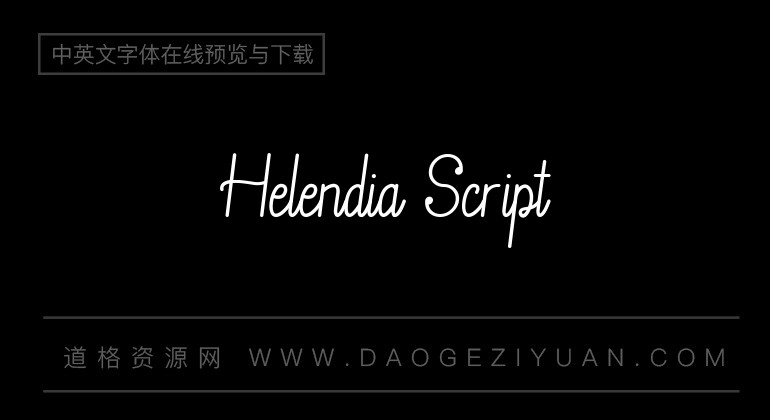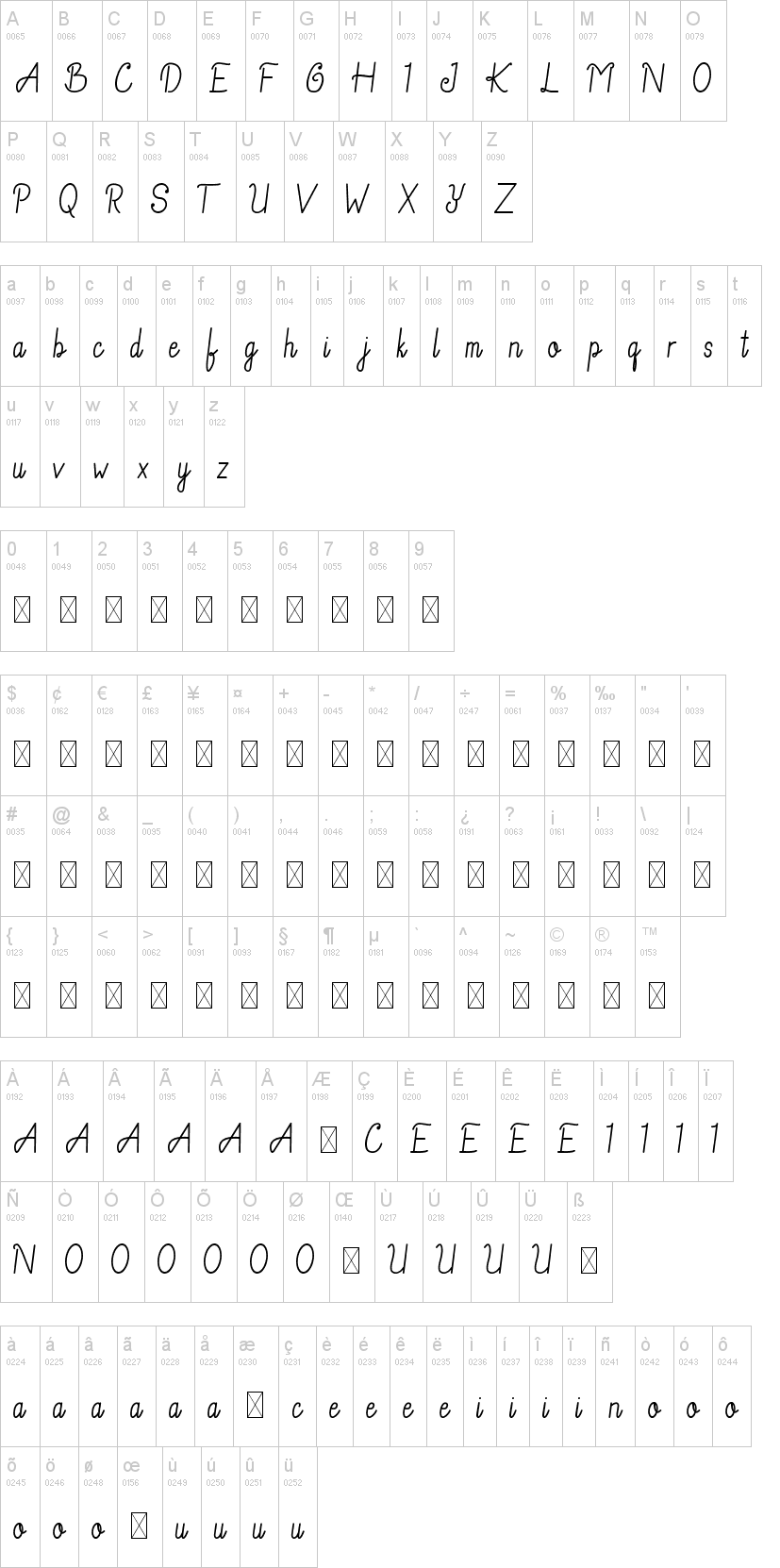
Helendia Script 是一款现代脚本字体,由 Helendia 字体设计师创作。它具有细腻曲线、流畅笔触和优雅外观,是一款华丽而优美的字体,可以用于各种海报、标识、书籍封面等设计中,给设计师带来无限的创作灵感。内容介绍
Helendia Script是一款非常不错的手写艺术字体,具有很好的视觉感,适合于文化类的宣传设计、商业类品牌的广告和产品包装设计以及个性化文字排版等较多场景。